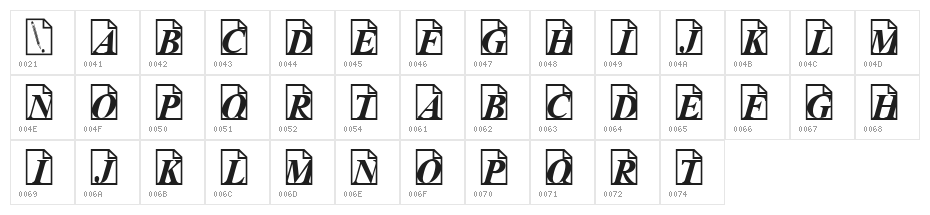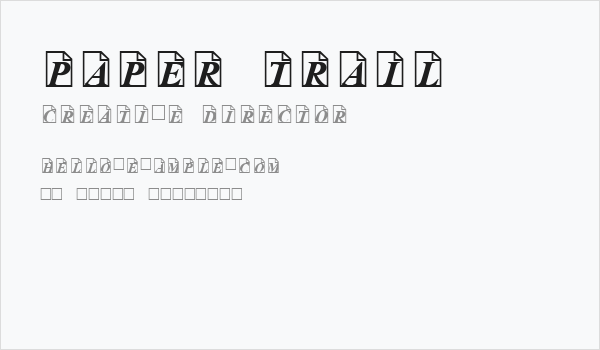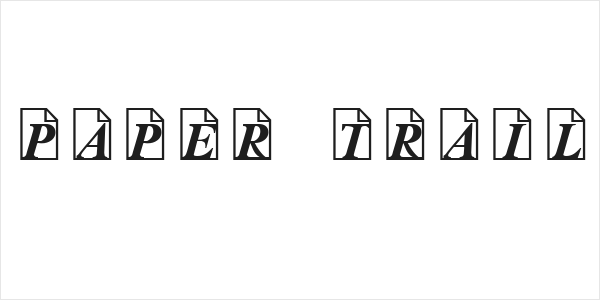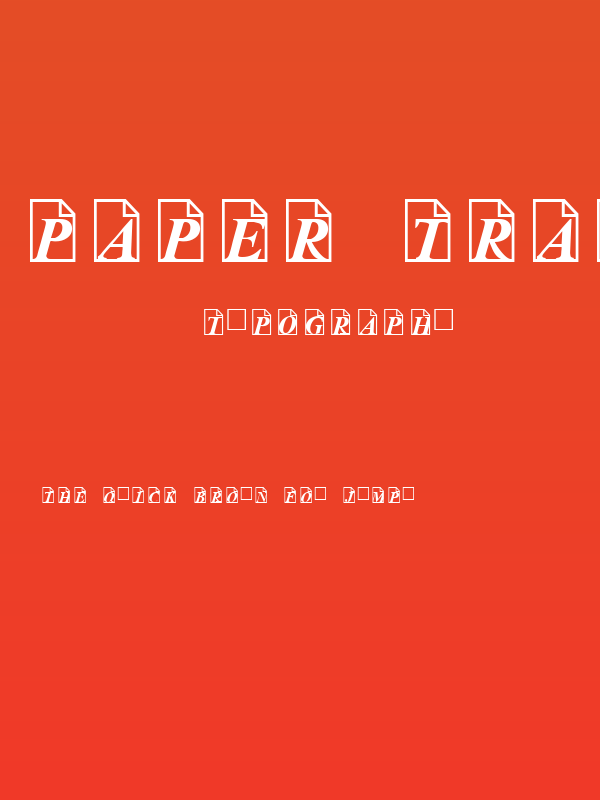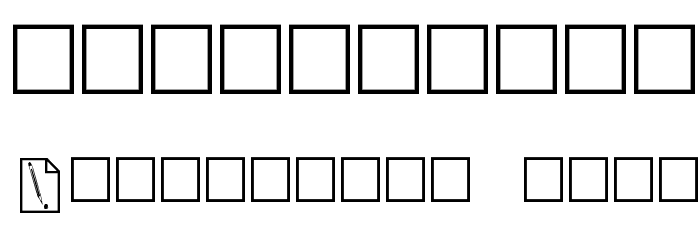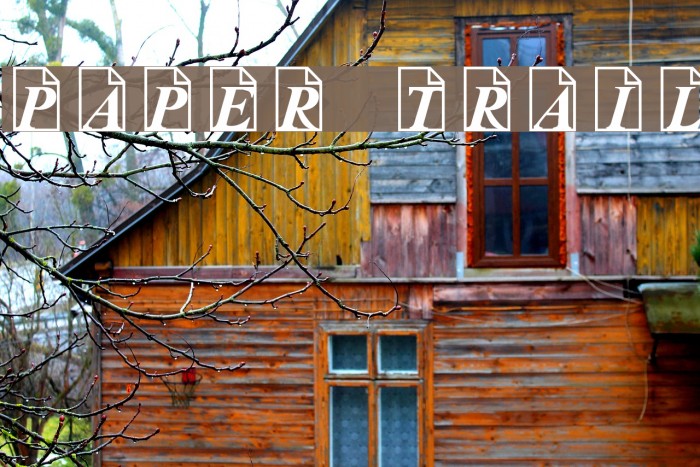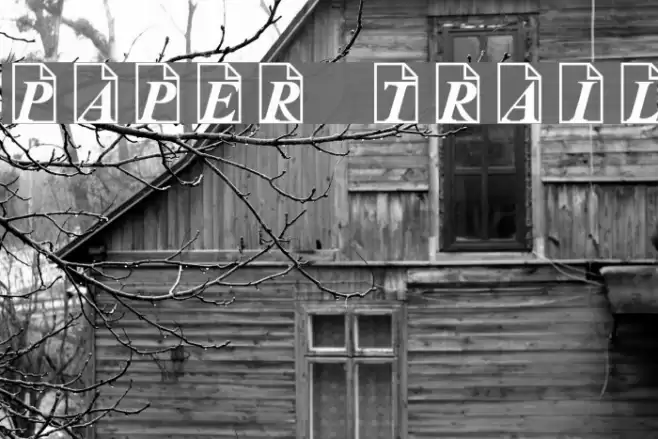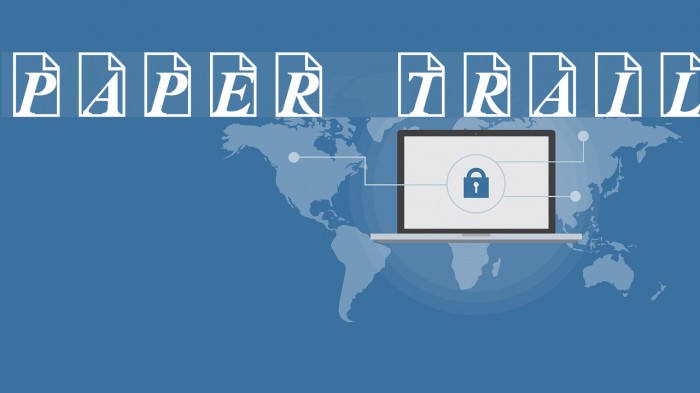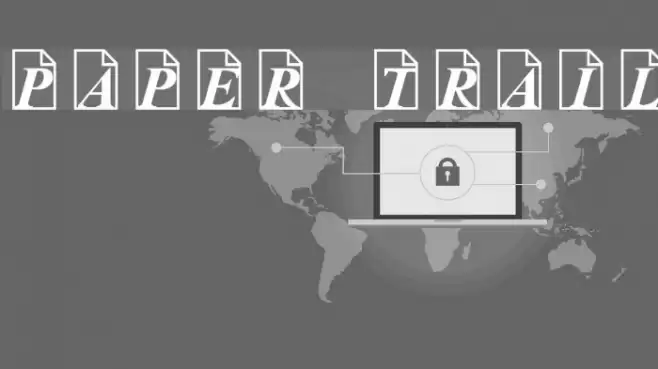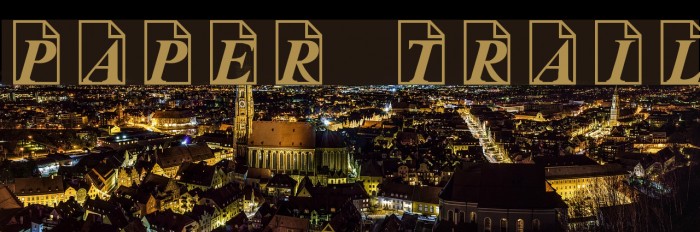
Paper Trail Font
| Caz de utilizare | Logos, Headlines, Creative projects |
| Proiecte propuse | Ideal for creative projects, educational materials, or playful branding that emphasizes organization or documentation themes. |